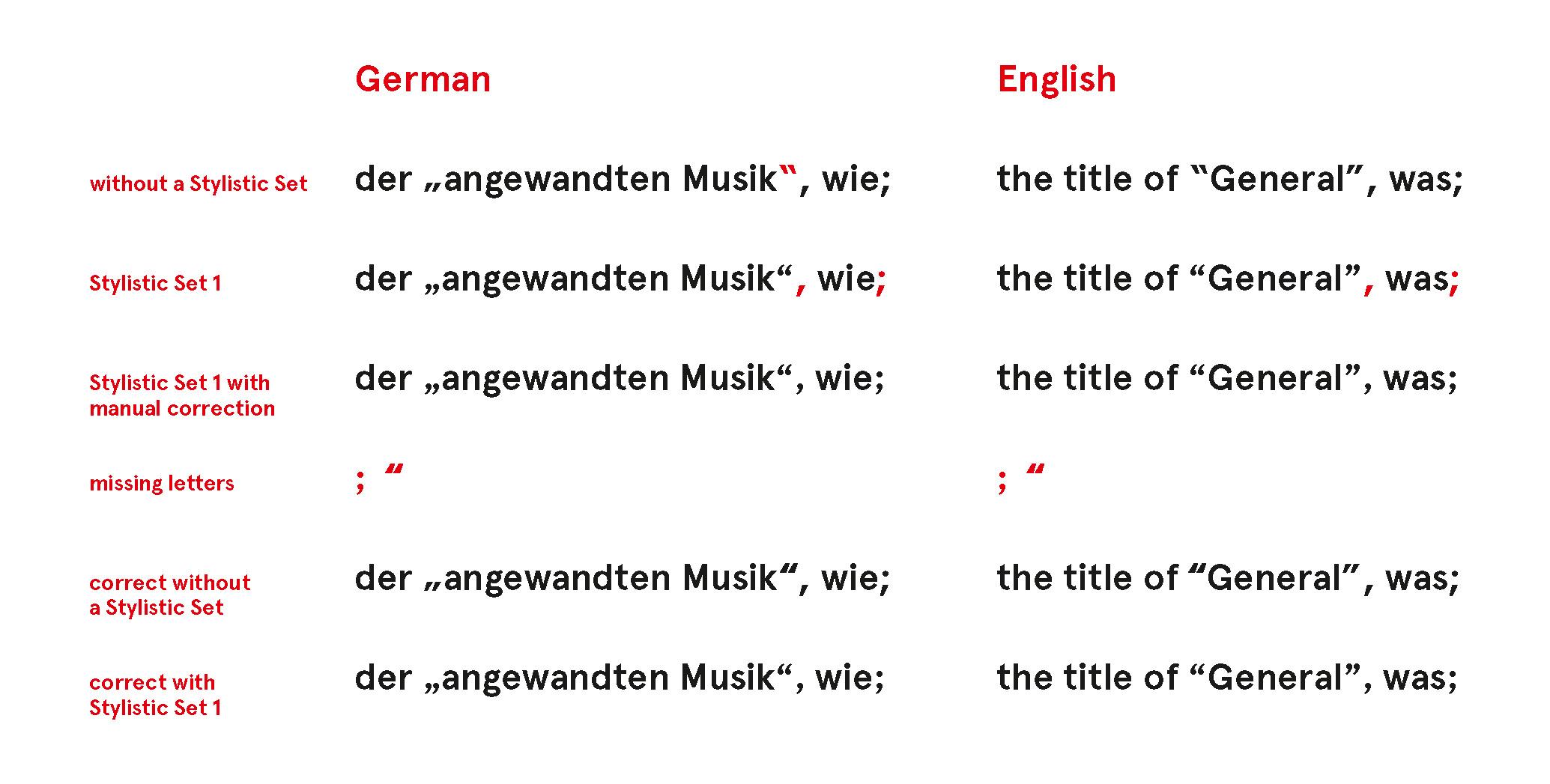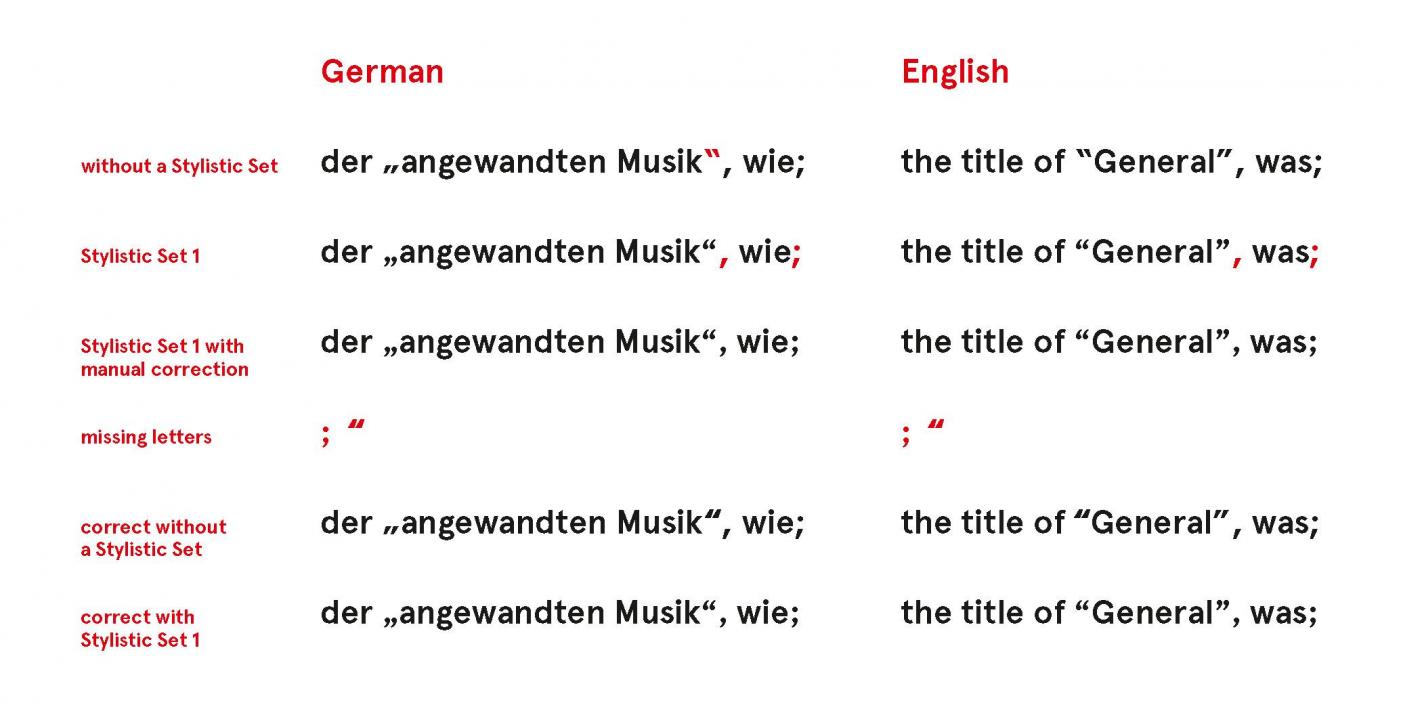
Probleme mit Apercu - fehlende Zeichen
Ich habe vor ein paar Tagen einen Schnitt der Apercu von Colophon lizenziert. Jetzt musste ich festellen, dass die Anführungen nicht korrekt sind und auch das Stylistic Set 1 nicht wie gewünscht funktioniert und die eckigen Anführungen und ähnliches in runde ändert. Bei einem Pro-Schnitt für 50 Pfund ist man da schon etwas genervt - zumal das Produkt morgen in Druck geht und ich jetzt manuell alles anpassen musste.